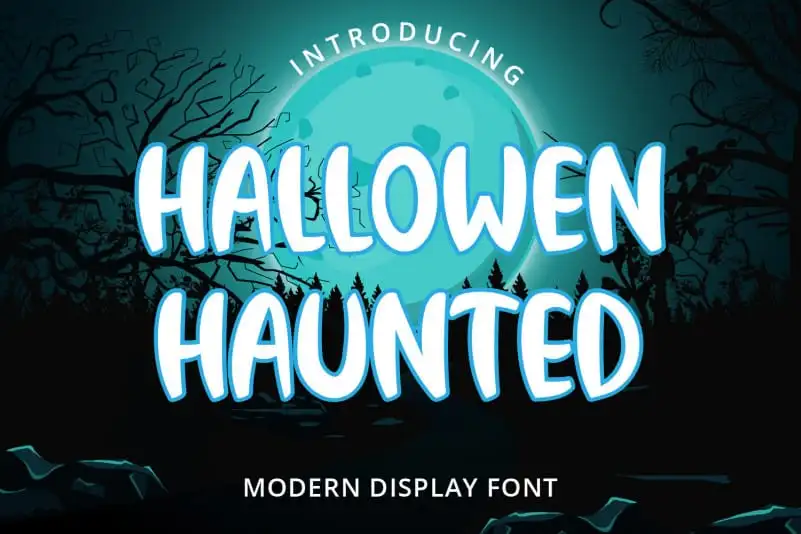
Hallowen Haunted Display Font – Download Grátis
A fonte “Hallowen Haunted Display Font” é uma escolha simples e elegante para criar design visual impactante. Suavemente tipográfica, ela se destaca nas composições de texto. O designer planetz studio criou um recurso gráfico único para eventos de Halloween ou qualquer ocasião que precise de uma letração impressionante. Este font é perfeito para aqueles artistas digitais buscando dar uma carona única a seus projetos, seja em cartazes de festivais, logomarcas ou materiais promocionais. Com sua elegância e simplicidade, “Hallowen Haunted Display Font” se destaca como uma fonte ideal para destacar o seu próximo trabalho. Tornará suas ideias criativas realmente notáveis e enriquecerá seus designs digitais de forma autêntica. Em um mundo de gráficos digitais cada vez mais competitivo, esta é uma escolha certeira que fará sua marca.